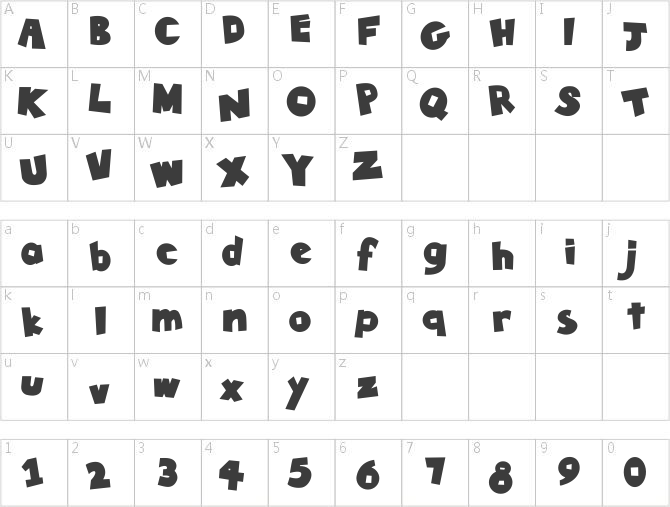
Tiki Tropic Bold
Tiki Tropic Bold介紹
Tiki Tropic Bold字體字庫是一款讓人賞心悅目、百看不厭的英文字體,適合各類廣告和產(chǎn)品包裝設(shè)計(jì)應(yīng)用,字體大小0.14MB,格式為ttf字體,上傳用戶是曾紹文,作者/版權(quán)方為未知